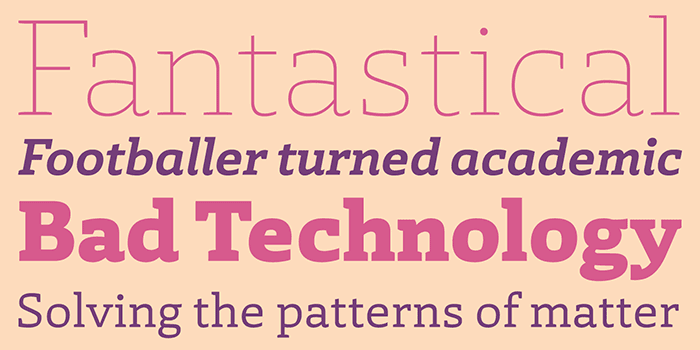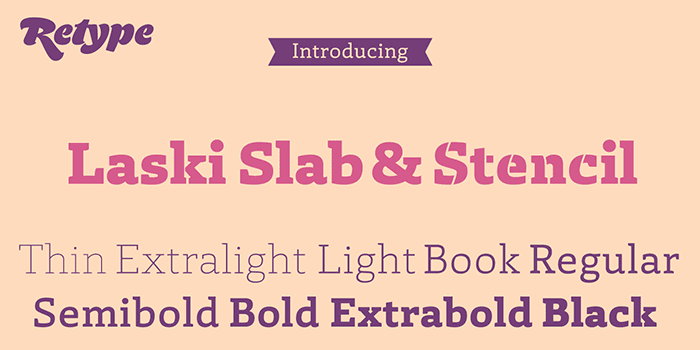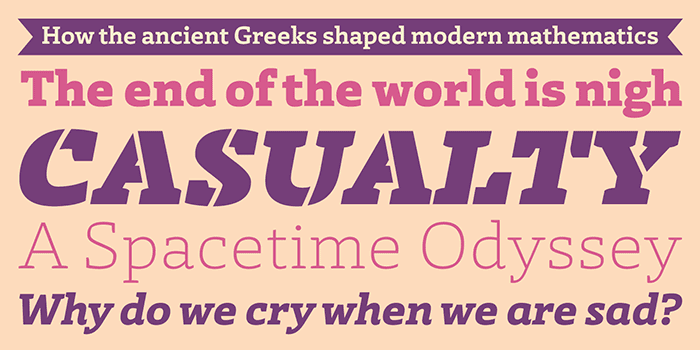
- slab
- Antiqua humanistisch
Die Laski Slab der argentinischen Designerin Paula Mastrangelo entstand zunächst als Abschlussarbeit ihres Schriftgestaltungsstudiums und zielte auf eine Anwendung in einem Online-Magazin für Kinder ab. Später wurde die Familie in Zusammenarbeit mit Ramiro Espinoza zu einer großen und vielseitig einsetzbaren Schriftfamilie ausgebaut und erschien 2014 bei Espinozas Label Re-Type.
Die Familie besteht aus neun Strichstärken mit Kursiven. Zusätzlich gibt es zwei dekorative Schablonenschrift-Versionen der Black-Schnitte. Die Schnitte mit jeweils über 700 Glyphen besitzen eine erweiterte lateinische Belegung mit Kapitälchen und verschiedenen Ziffernsets.